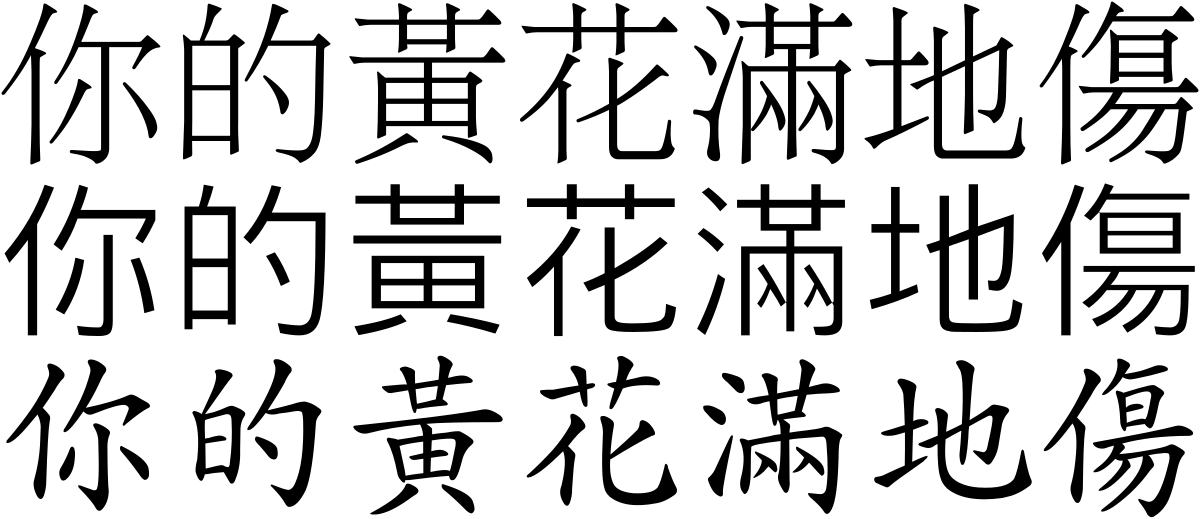
Как использовать традиционный китайский шрифт в css?
Я пытаюсь отобразить какой-то текст на традиционном китайском языке на своем сайте.![]()
HTML:
<div id = "shareText">好</div>
CSS:
#shareText
{
position: absolute;
right: 125px;
padding: 20px 0 0 0;
color: #a9a4a4;
font-size: 25px;
}
Однако выходной символ, который я получаю, таков: 好. Я устал менять шрифт вот так:
#shareText
{
position: absolute;
right: 125px;
padding: 20px 0 0 0;
color: #a9a4a4;
font-size: 25px;
font-family: "微軟正黑體", "Microsoft JhengHei", Tahoma , Verdana , Arial , sans-serif;
}
Однако характер остается прежним. Что я делаю не так? Это как-то связано с кодировкой файла html? Я попробовал перейти с unicode 8 на 16, символ появляется, но я теряю все форматирование, все мои дивы находятся не в том месте..
Firefly, шрифт с низким разрешением
Одно технологическое изменение — разрешение экрана. До недавнего времени экраны не могли обрабатывать тонкие изгибы и петли, характерные для более каллиграфического китайского языка. Фактически, на заре компьютеров все китайские иероглифы, кроме простейших, не могли быть представлены точно или даже разборчиво.